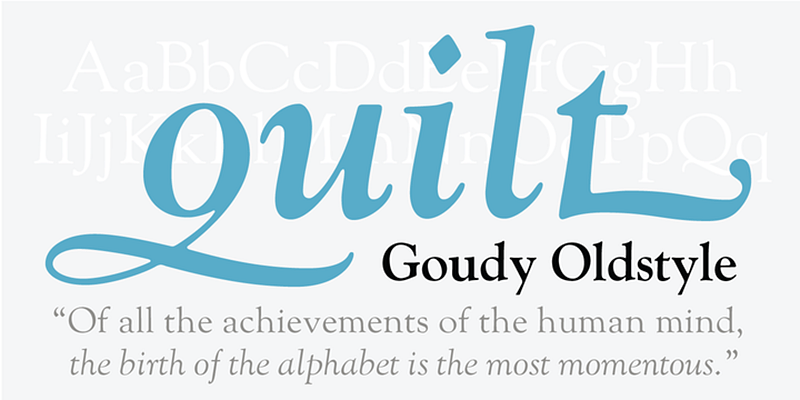
LTC Goudy Oldstyle ist ein klassisches Design von Frederic W. Goudy. Die OpenType-Schriftart umfasst lange oder kurze Unterlängen und viele andere Alternativen.
Die Wurzeln von Lanston Type Co. (LTC) gehen auf die Lanston Monotype Company von 1887 zurück, die von Tolbert Lanston, dem Erfinder der Monotype-Gießmaschine, gegründet wurde. Nach der Trennung von seinem englischen Pendant hatte LTC Probleme und wurde mehrmals verkauft, an American Type Founders, Hartzel Machine Works, Mackenzie & Harris und Gerald Giampa. Im Jahr 2004 übernahm P22 Type Foundry die Firma und beherbergt heute klassische Designs von Frederic W. Goudy und Sol Hess sowie die neueren zeitgenössischen Meister Giampa, Jim Rimmer und Dave Farey.